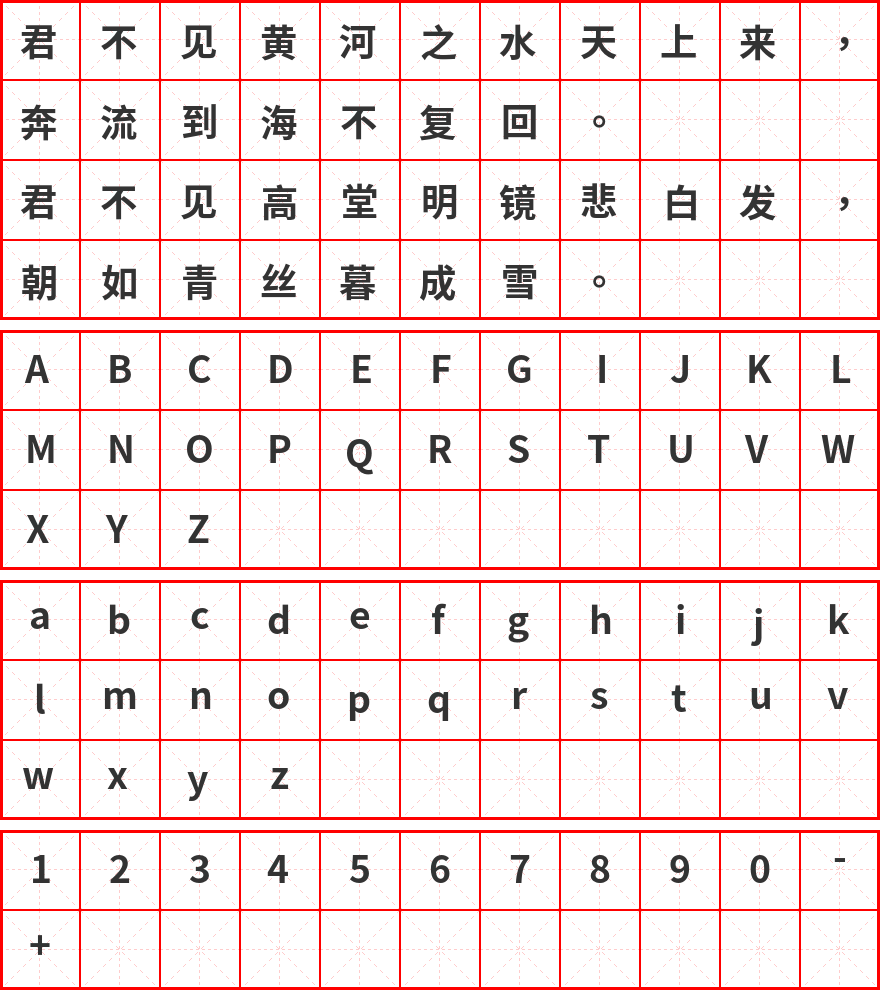
思源黑体 SourceHanSansSC-Bold
思源黑体
思源黑体 BOLD 是思源黑体字体系列中的粗体变体,由 Adobe 和 Google 合作开发。以下是其详细介绍:
• 基本信息:思源黑体于 2014 年 7 月推出,是一款开源字体,旨在提供高质量的多语言支持。思源黑体 BOLD 是该字体家族中用于强调内容的字体,具有较粗的笔画,在 Adobe 版本中显示的字体名称为 “思源黑体”,字重名称为 “Bold”;在谷歌版本中显示的字体名称是 “Noto Sans CJK”,字重名称为 “Bold”。
• 字体特点:思源黑体 BOLD 通过加粗的笔画增加了文本的视觉重量,在保持思源黑体整体风格一致性的同时,使其在页面上更加吸引眼球,能够有效突出显示内容。
• 字符集支持:思源黑体 BOLD 完全支持繁体中文、简体中文、日文和韩文,还包括拉丁文、希腊文和西里尔文字形,可满足多语言排版需求。
• 应用场景:思源黑体 BOLD 适用于多种场景,如品牌设计中可增强品牌识别度;出版物中用于标题或强调文字,增强视觉冲击力;数字媒体中可用于按钮、标题等,提高用户体验;教育材料和学术论文中可用于标题和关键词,帮助读者快速定位重要信息。